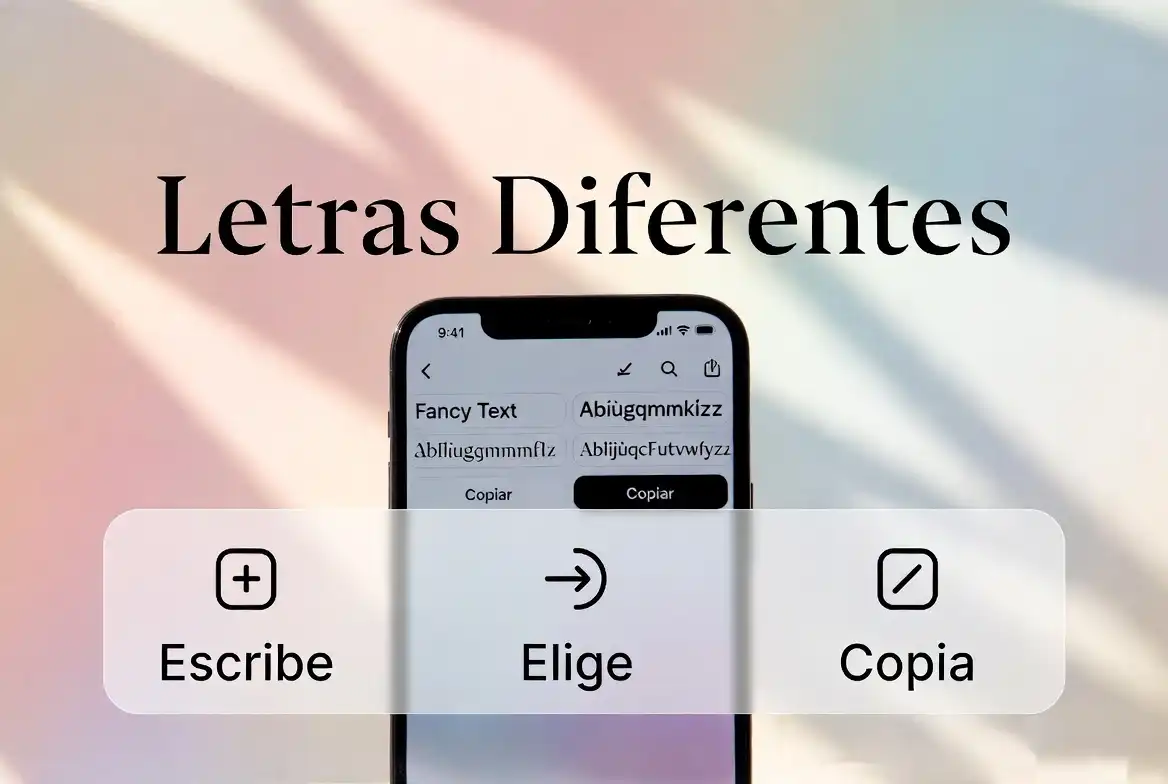
Explora letras diferentes y estilos de texto únicos que puedes copiar y pegar fácilmente en cualquier lugar. Solo escribe tu texto, elige entre más de 100 estilos y usa el que más te guste en Instagram, WhatsApp, Facebook y otras redes sociales.
Las letras diferentes son perfectas para nombres, biografías, mensajes y publicaciones que quieran destacar con un estilo único y creativo.
Escribe tu texto Letras → Vista previa: ʟᴇᴛʀᴀꜱ, ༺♡ 𝙻𝚎𝚝𝚛𝚊𝚜 ♡༻, 𝓛𝓮𝓽𝓻𝓪𝓼 → Copiar → Pegar en: Instagram, Facebook, WhatsApp.
Las letras diferentes son estilos de texto creados con caracteres Unicode que permiten transformar las letras normales en estilos únicos y llamativos. Se utilizan principalmente para crear nombres, biografías, mensajes y publicaciones más atractivas en redes sociales como Instagram, WhatsApp, Facebook y TikTok.
1. Nombres con letras diferentes (estilo español)
2. Letras diferentes aesthetic
3. Letras diferentes para Instagram
4. Letras diferentes bonitas
5. Letras diferentes para juegos
6. Frases con letras diferentes